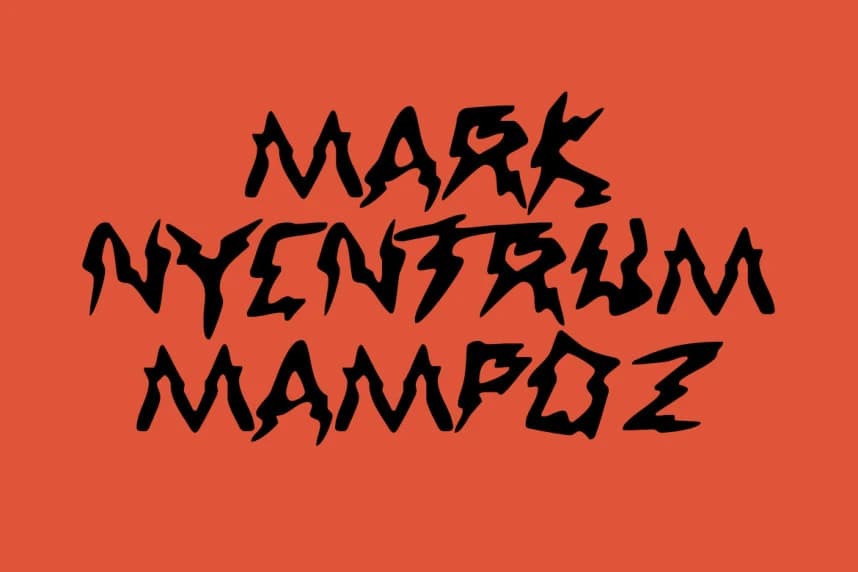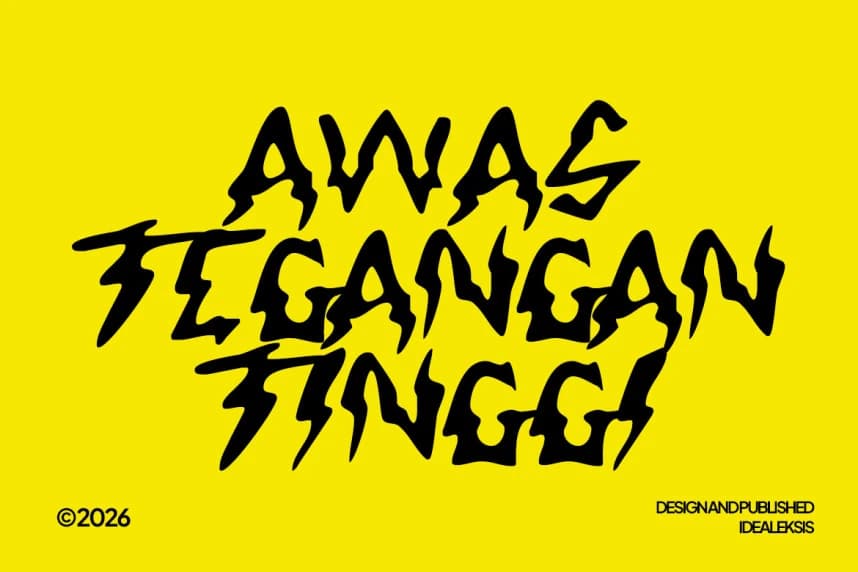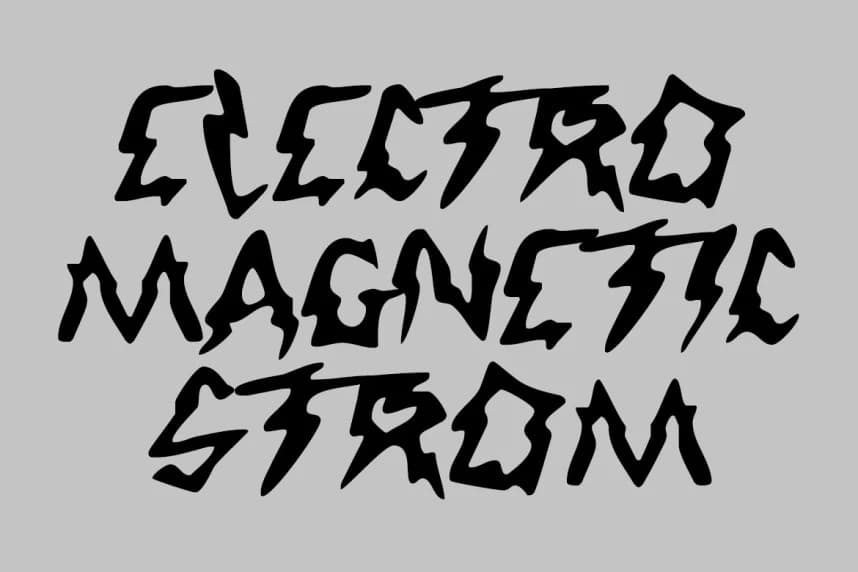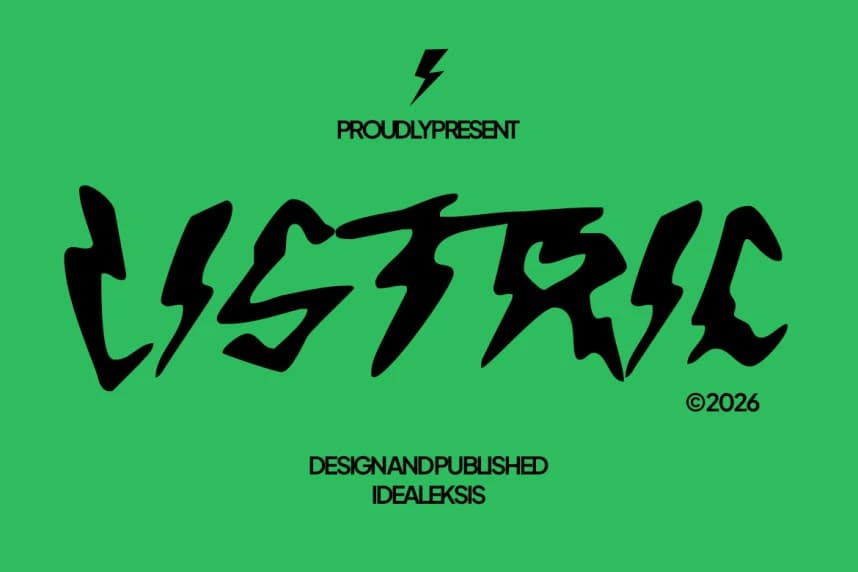
Listric Display Font
Listric Display Font, elektrik enerjisiyle dolu cesur ve keskin hatlı bir gösteri tipi yazı tipidir. Keskin kenarları ve açılı çizgileri, bir şimşeğin gücünü yansıtarak yazıya dinamik ve asi bir karakter kazandırır.
Listric Display Font, elektrik enerjisiyle dolu cesur ve keskin kenarlı bir gösteri yazı tipidir. Kenarları keskin ve açısal hatlar, şimşeğin gücünü yansıtarak fonta dinamik ve asi bir karakter kazandırıyor.